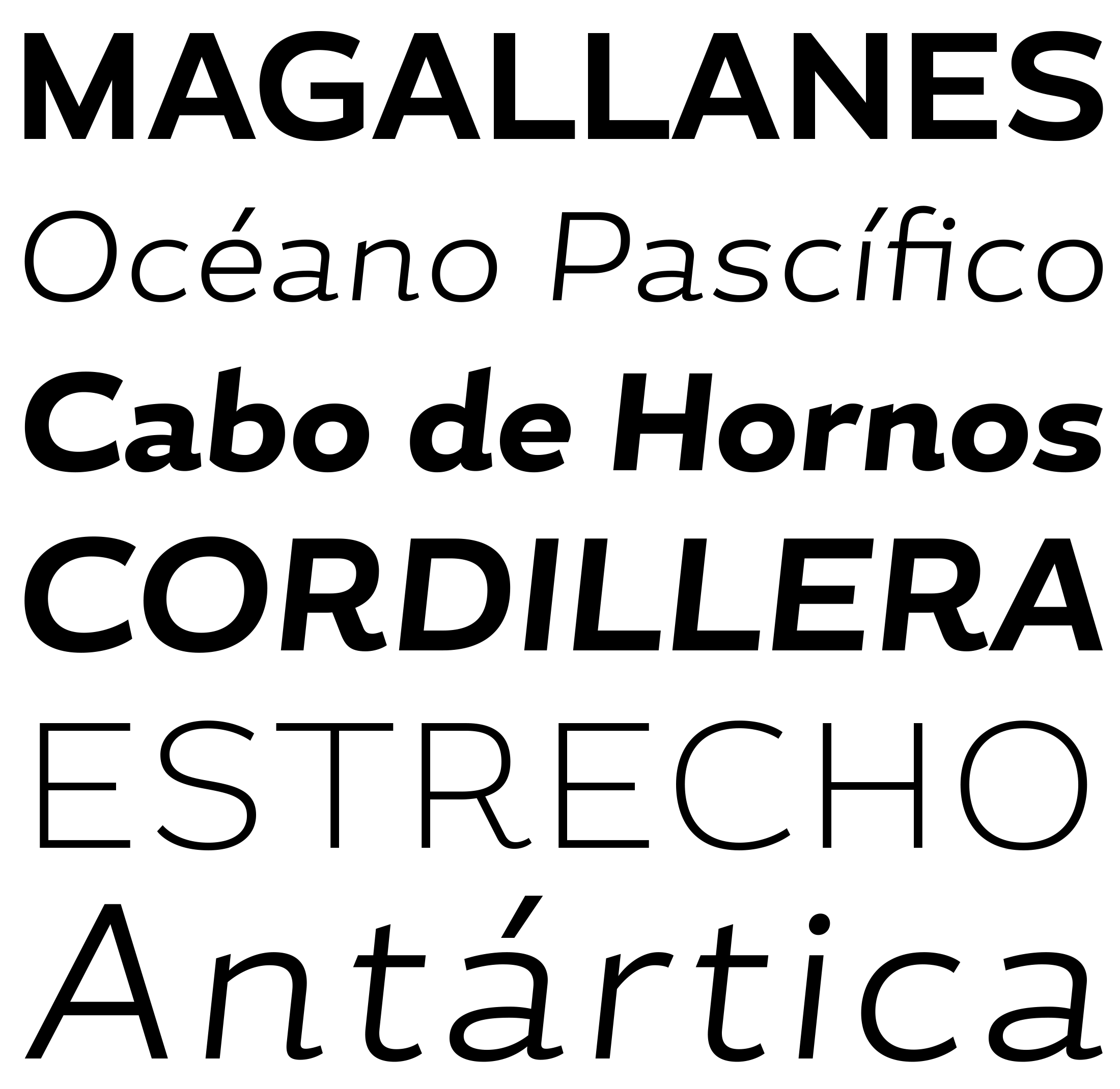
Magallanes
| Año | 2013 |
| Créditos | Daniel Hernández |
| Descripción | Magallanes es un tipo de letra sans-serif neohumanista contemporáneo diseñado por Daniel Hernández. Cada estilo incluye glifos alternativos que proporcionan una amplia gama estilística. |
| Clasificación | Texto |
| Estilos | 18 |